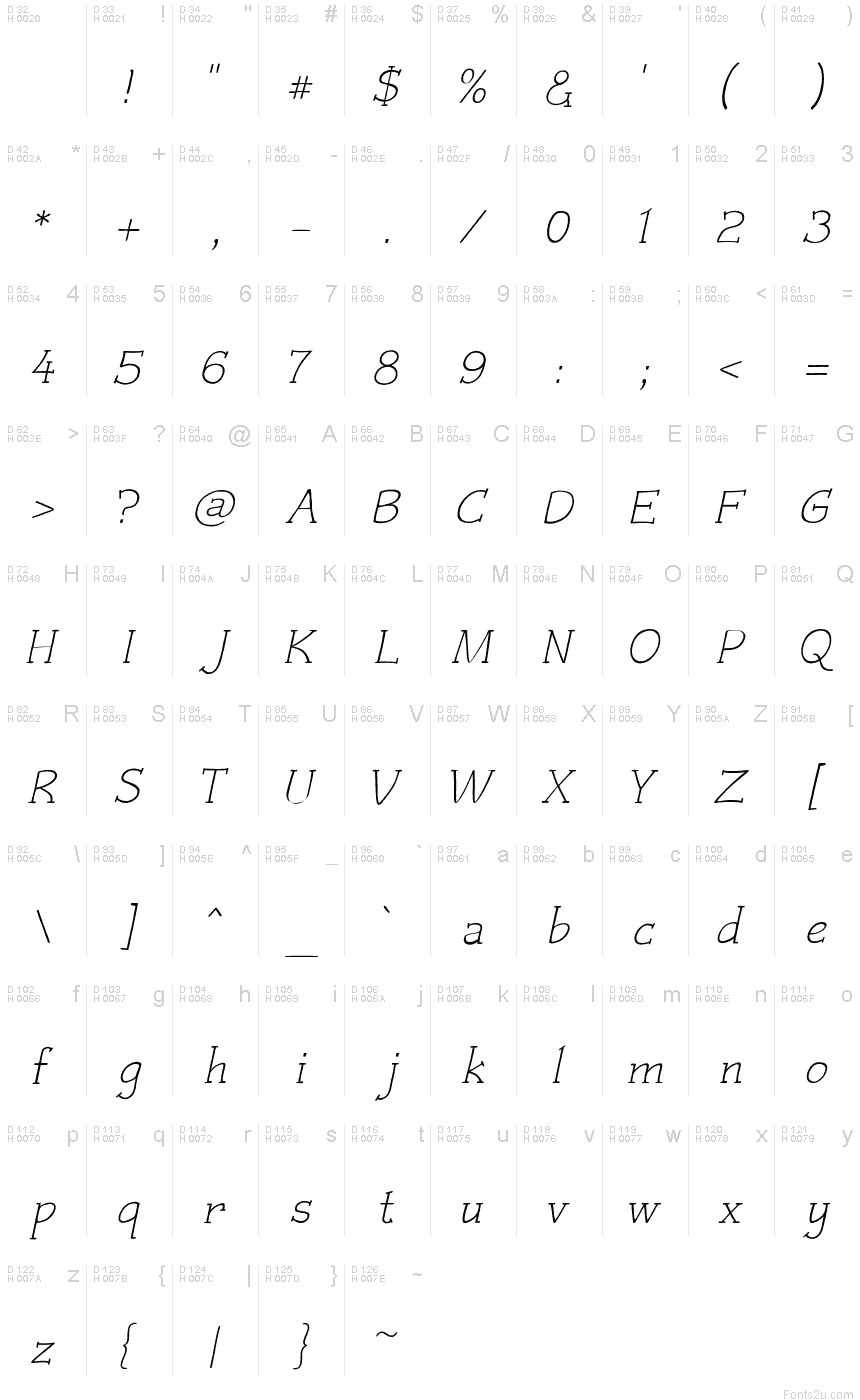
Czaristite Oblique
Czaristite Oblique autorstwa Grahama Meade’a wnosi do rodziny Czaristite elegancki, „zamoczony w tuszu” pochyły styl, który sprawia wrażenie odręcznego pisma, pozostając przy tym czystym i zrównoważonym. Pociągnięcia są smukłe i wyraziste, z drobnymi akcentami, co nadaje nagłówkom zabawny, lekko teatralny rytm bez efektu niechlujstwa. Czaristite Oblique to darmowy, dekoracyjny krój szeryfowy w stylu komiksowym; przy dużych rozmiarach jego żywe kąty są natychmiast czytelne.
Używając Czaristite Oblique, uzyskasz wyrazisty efekt na plakatach, okładkach książek, początkach rozdziałów, menu kawiarni, zaproszeniach, logotypach, grafikach z cytatami i opakowaniach małoseryjnych. Zachowaj prosty układ strony, aby pochyły styl mógł mówić sam za siebie, i zestaw ten darmowy krój z prostym bezszeryfowym pismem, takim jak Inter lub Helvetica, w tekście głównym i podpisach.